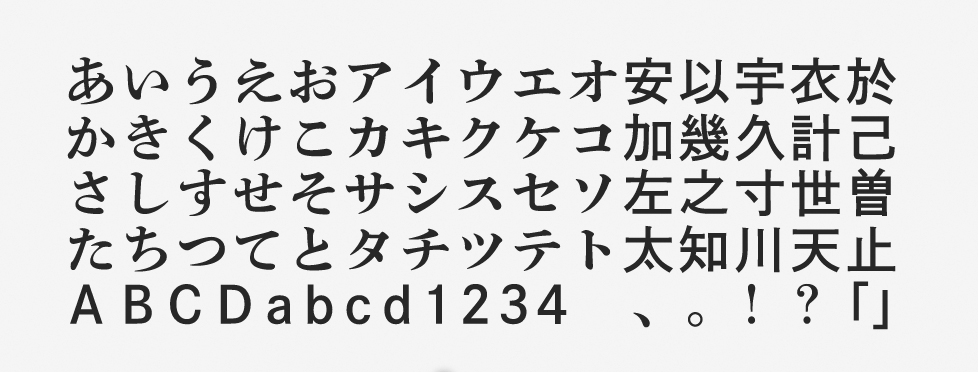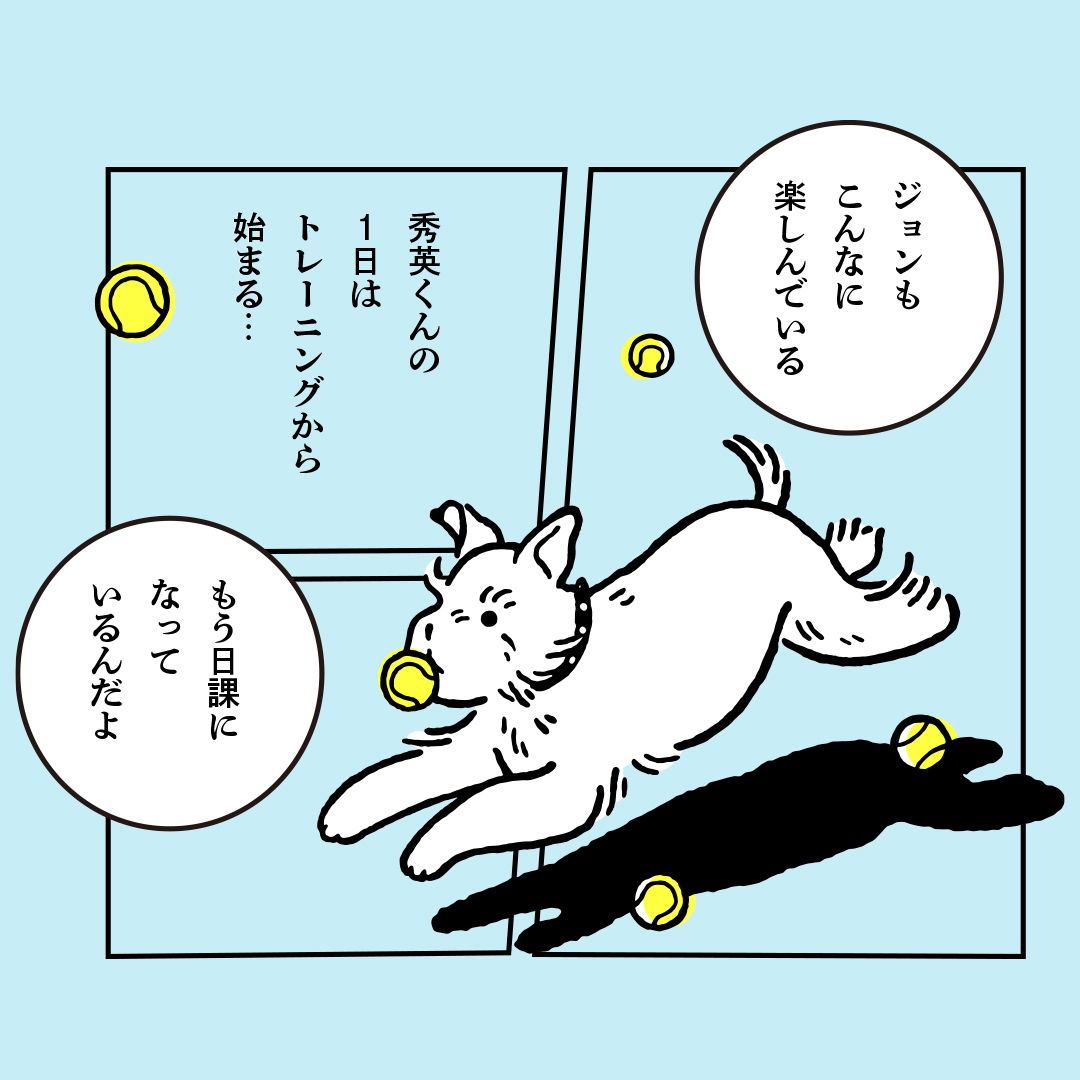
「秀英アンチック+」について
明朝デザインのかな文字にゴシック体の漢字が混植されています。本来は仮名および一部の記号類のみであった「秀英アンチック」と、「秀英角ゴシック」の漢字や英数字が組み合わせられています。「秀英アンチック」は、大日本印刷オリジナルのアンチック体を復刻した書体です。
「秀英アンチック+」の特徴
このような混植はアンチック体(アンチゴチ)と呼ばれ、特に漫画の吹き出しの文字で多用されています。秀英アンチック+は、わざわざ合成フォントを作成することなくそのままスムーズに打ち出すことができて、使い心地が抜群です。
「秀英アンチック」には、感情を込めて肉声で話しているかのような重厚な力強さがあります。大ぶりで安定感があることも特徴です。そこへクラシックな表情の「秀英角ゴシック」を加え、アンチゴチ利用に最適な設計が施されています。
漫画のセリフとして、かなりの親しみのあるフォントでしょう。「い・こ・に」など、「筆跡」を強く感じさせるデザインの仮名が多く、漫画のセリフには多い縦書き形式にもよく合います。一方で、横組みでも使っても違和感はありません。アンティークな雰囲気も出しやすいフォントです。